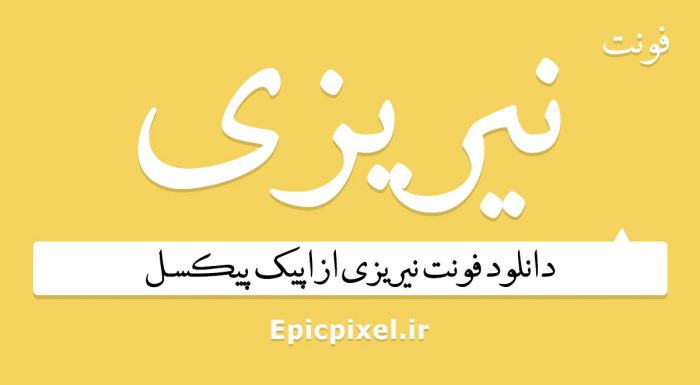
فونت نیریزی فارسی
| ⭐ توضیحات | فونت نیریزی یکی از بهترین فونت هایی هست که می تونین برای نوشتن متن های قرآنی ازش استفاده کنین همینطور شما می تونین فونت دعایی اسلامی نیریزی رو برای نوشتن حدیث ها و دعاهای عربی بکار ببرین که قطعا یه زیبایی خیلی خاصی به نوشته هاتون میده طوری که فکر می کنین این یه فونت دست نویس کشیده است!
البته فونت نیریزی کشیده نیست و ربطی به فونت های کشیده نداره اما سبک و قطر و قلم این فونت خیلی شبیه به فونت های کشیده هست. اگه یکم دقیق تر به دستخط و کش و قوس های این فونت نگاه کنین متوجه شباهت های فرمی این فرم با دو تا فونت نسخ و فونت ثلث می شین و خوب این یعنی هرجا میشه از اون دوتا استفاده کرد کنارش این فونت هم قابلیت استفاده رو داره، مثل وقتی که میخواین یه تایپوگرافی یا یه کالیگرافی خفن بزنین و به یه فونتی نیاز دارین که هم صمیمی باشه و هم خوانا و هم خوش فرم.
فونت نیریزی ازکجا اومده فونت فارسی نیریزی رو آقا حسین زاهدی عزیز که کارشناس گرافیک هم هستن طراحی کردن، البته تمام زحمت های طراحی و اجرا و امتحان و عرضه این فونت روی دوش ایشون نبوده و به سفارش شورای عالی اطـلاع رسانی و ناظر کیفی کار استاد امیراحمد فلسفی بوده و خانم فرزانه یحیی پور اون رو اجرا کرده و نهایتا توی سال 1392 این فونت رو همراه یه مجموعه دیگه از فونت ها وارد دنیای دیجیتال کردن. این فونت دومین فونتی هست که شورای عالی اطلاع رسانی سفارش داده و تونسته یه دورگه به حساب بیاد یعنی چی؟ یعنی هم نماد فرهنگ و هنر ایرانی باشه و هم یک رسم الخط برای متن های اسلامی باشه و خب همین باعث شده که لقب «رسم الخط ایرانی-اسلامی» بهش بدن.